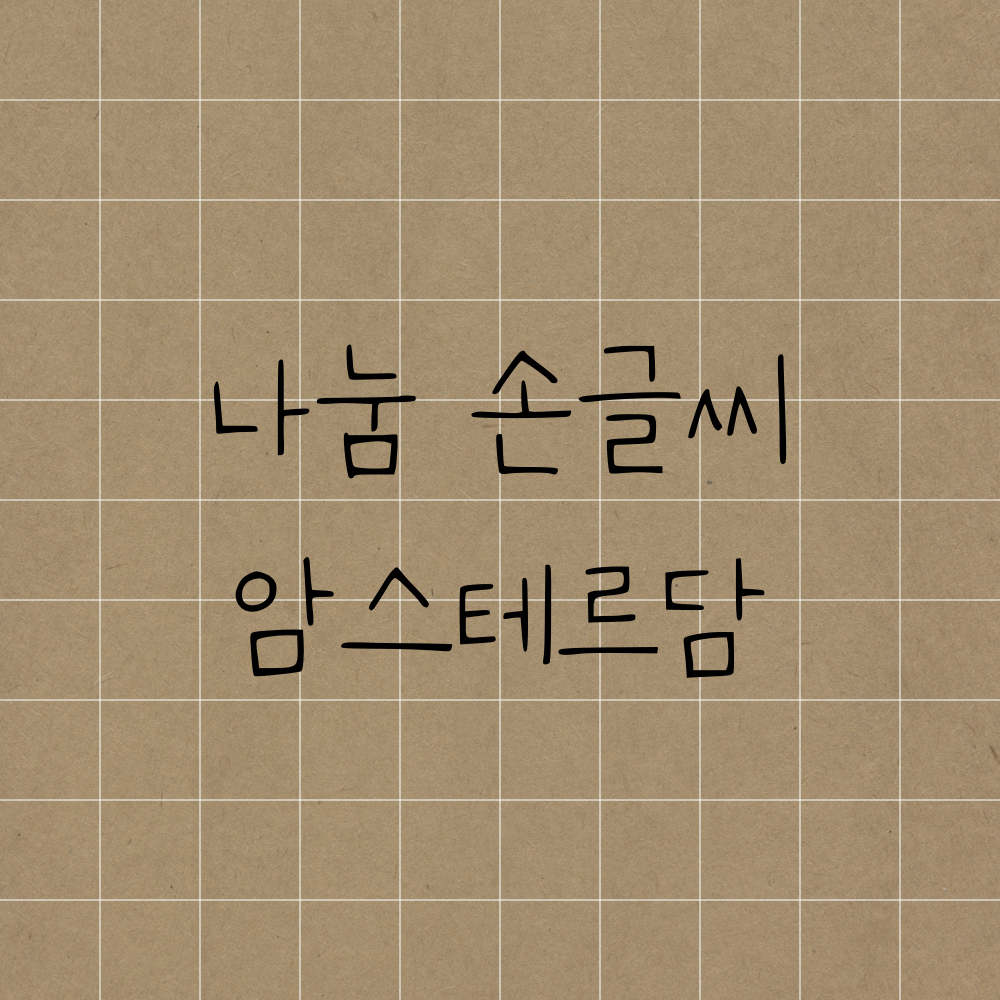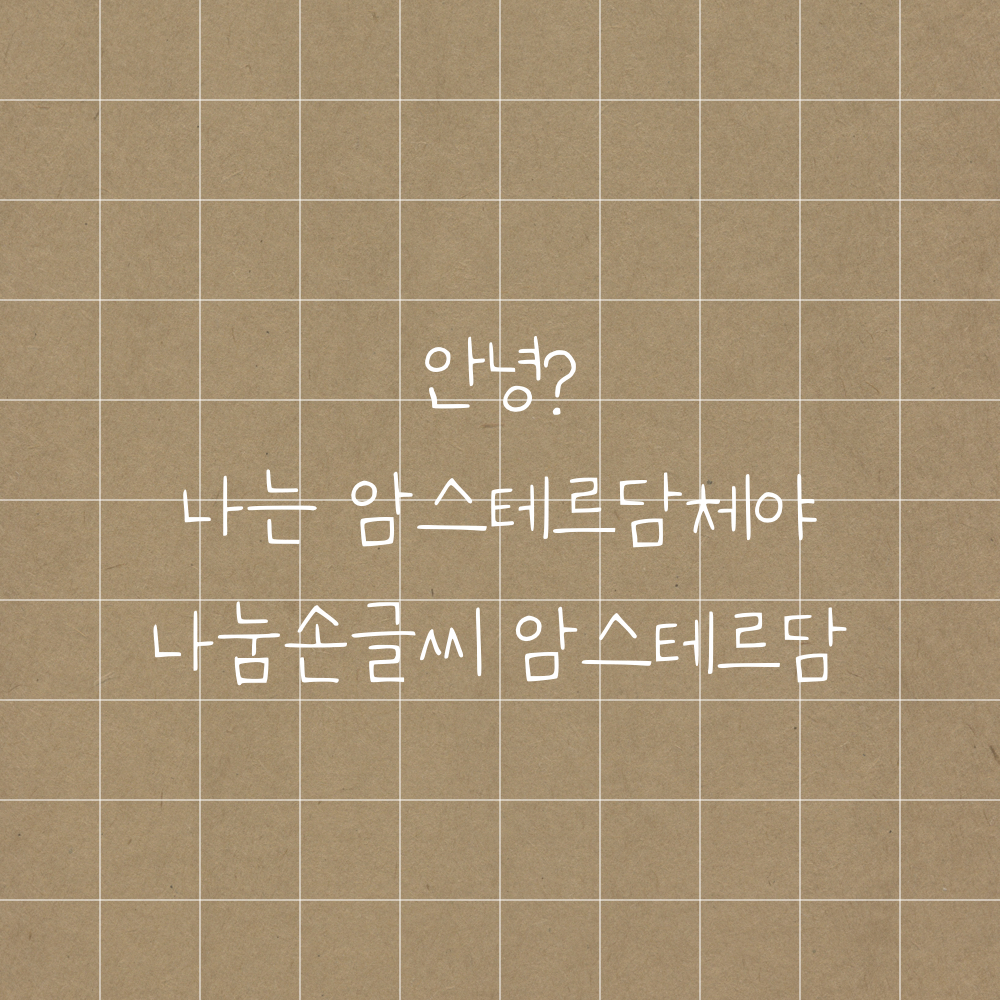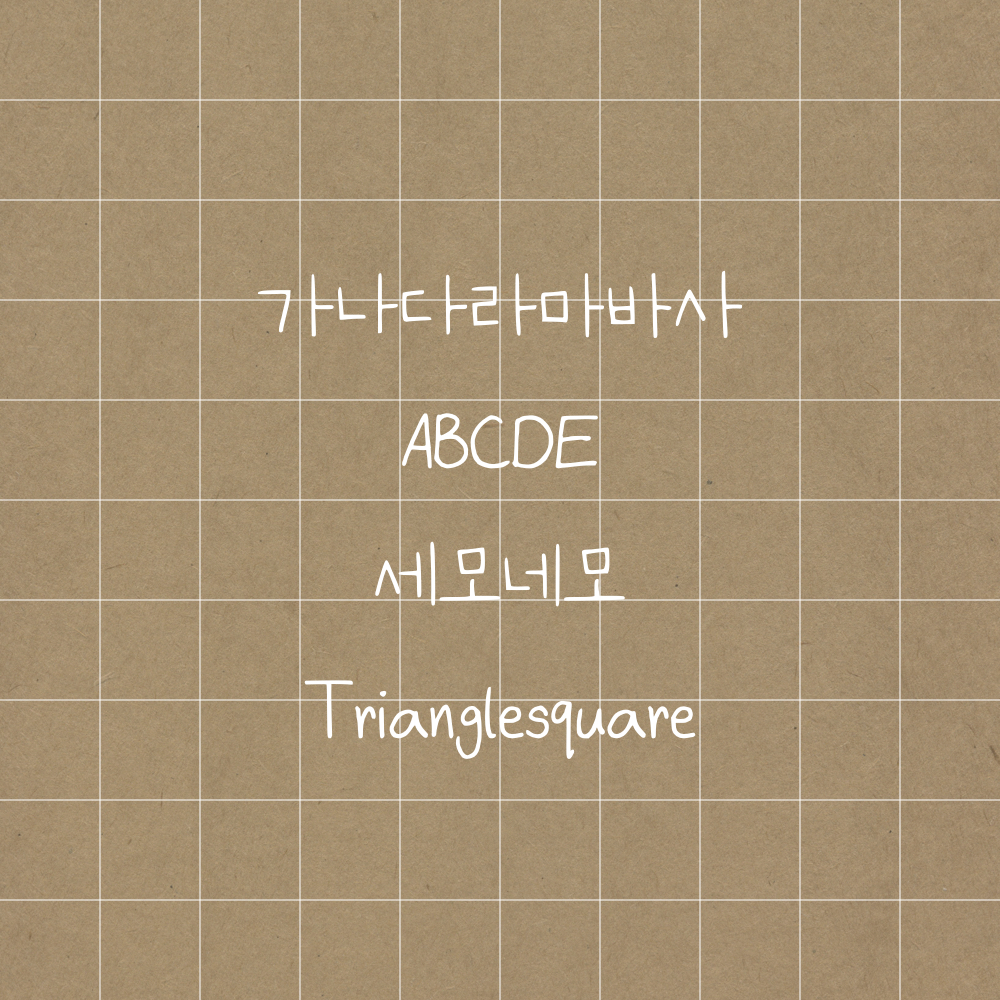
오늘의 폰트는 암스테르담입니다💜
다른 폰트보다 직선이 매력적인 폰트입니다.
저세상 반듯함으로 마음이 편안해지는 글씨체이니 집중해 주세요~!!
이런 글씨체를 가지려면 매일 연습해야 할 텐데
다운로드 한 번으로 글씨체를 바꿀 수 있다니,, 세상 너무 좋아졌네요..ㅎㅅㅎ
오늘 소개한 글씨체를 가지고 싶어서 연습했던 학생 때가 생각나네요😂
그땐 가지지 못했지만 태블릿에 폰트를 다운로드하여 결국 얻었습니다.😆